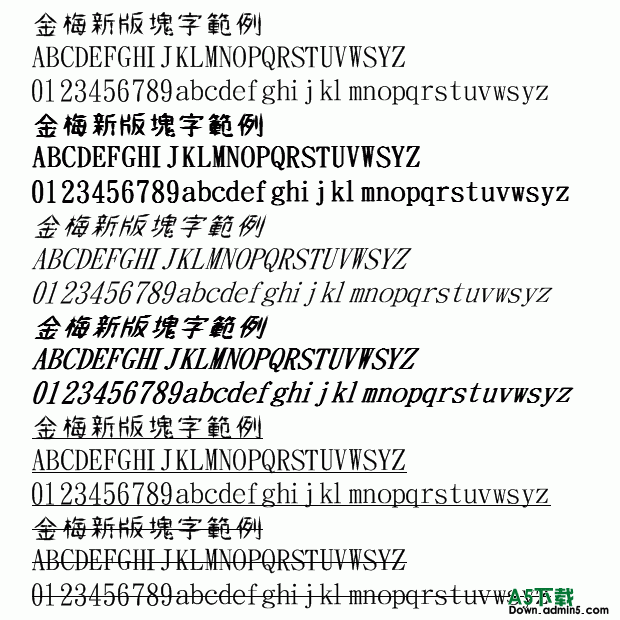
金梅新版塊字范例字體是由本站為大家所提供的一款字體軟件,當(dāng)然,這款字體也只是金梅字體中的一種而已,但是其應(yīng)用的范圍還是非常廣泛的,用戶們可以用來(lái)進(jìn)行廣告設(shè)計(jì)和書面文章排版等,非常的美觀,有需要的朋友可以來(lái)綠色資源網(wǎng)下載使用哦。